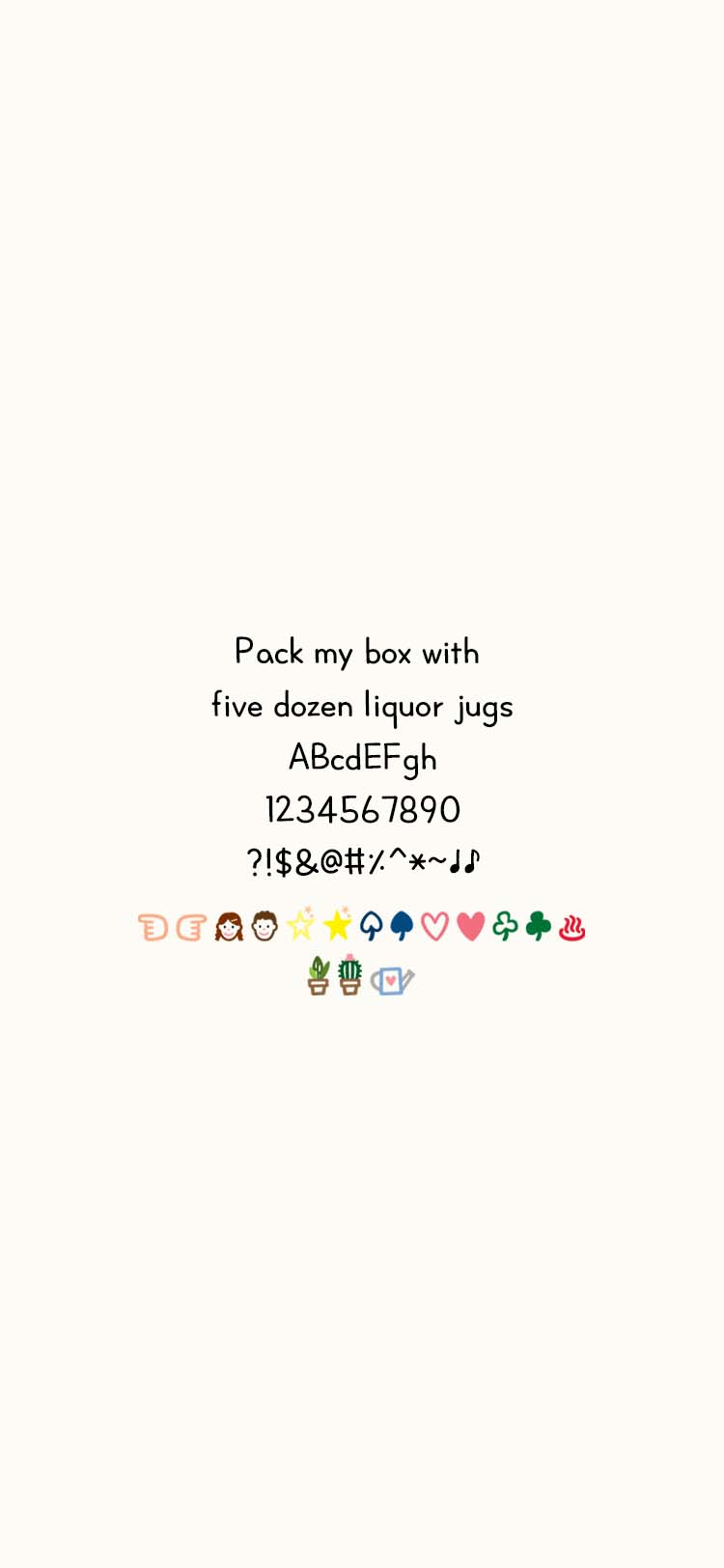
- ;), ;>, :!: 을 치면 작은 화초들이 있어요.
- ★☆☜☞♀♂♠♡♣♤♥♧♨에서 컬러 딩벳을 지원합니다.
- 라틴, 일본어(히라가나, 카타카나), 키릴문자를 지원합니다,.
- 한글 11,172자 / 라틴 94자 / 부호 1,300자 / 추가 글리프 3자
- Jj비밀의화원 / JjTheSecretGarden